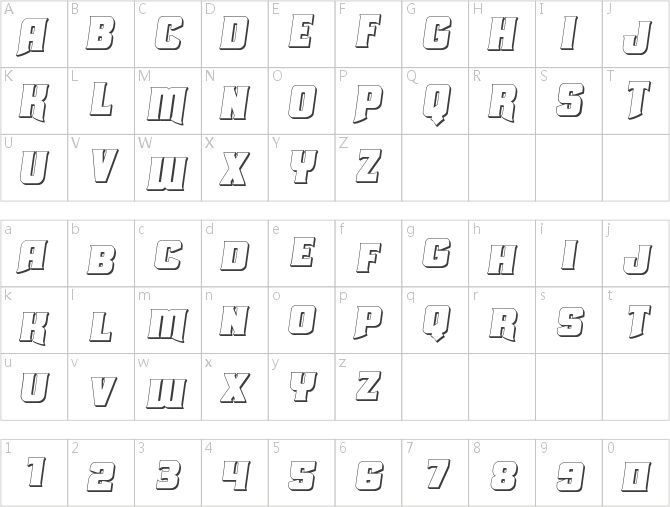
Union Gray 3D Semi-Italic
Union Gray 3D Semi-Italic介紹
Union Gray 3D Semi-Italic字體字庫是一款讓人賞心悅目、百看不厭的英文字體,適合各類廣告和產品包裝設計應用,字體大小0.07MB,格式為ttf字體,上傳用戶是快霸中國,作者/版權方為未知